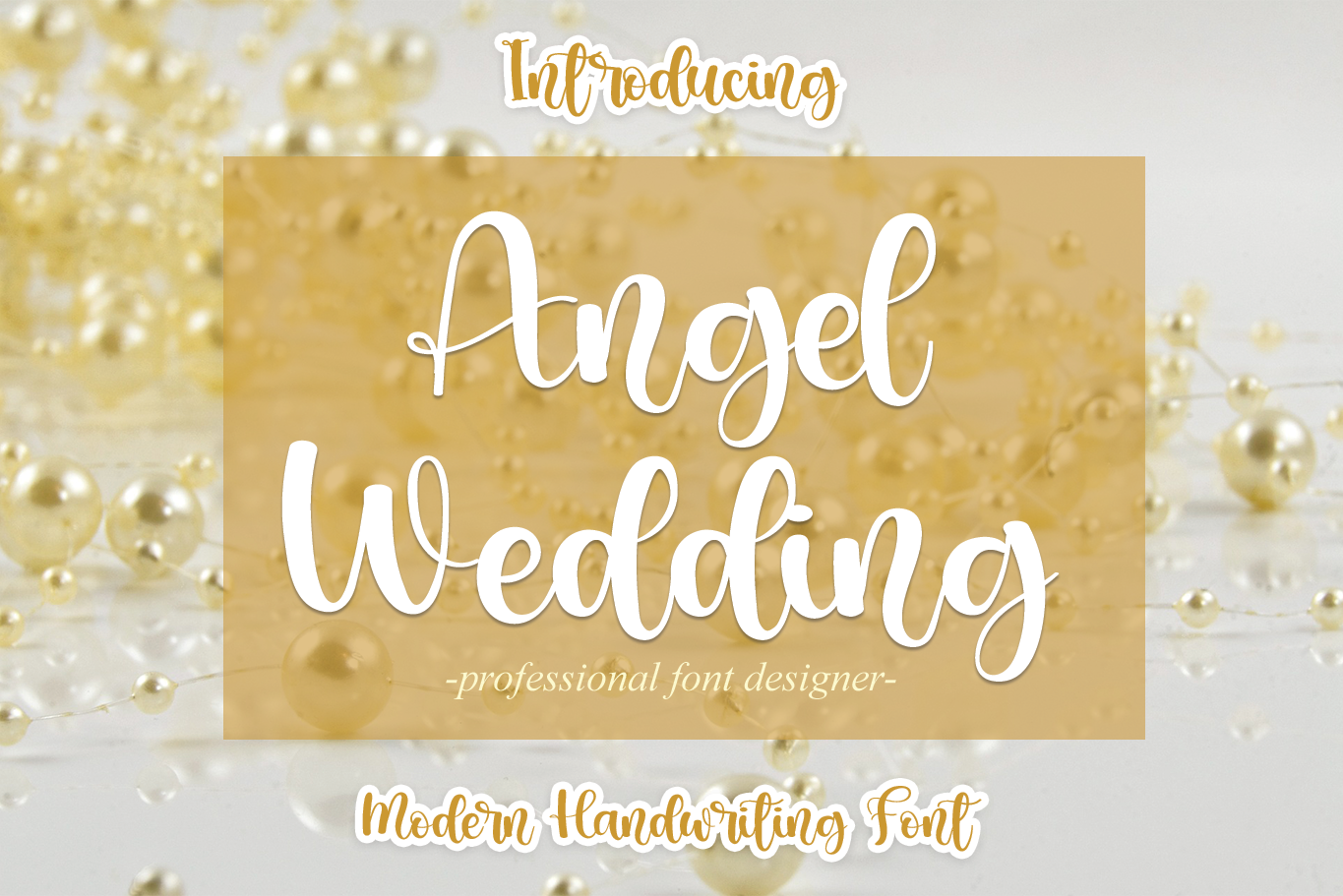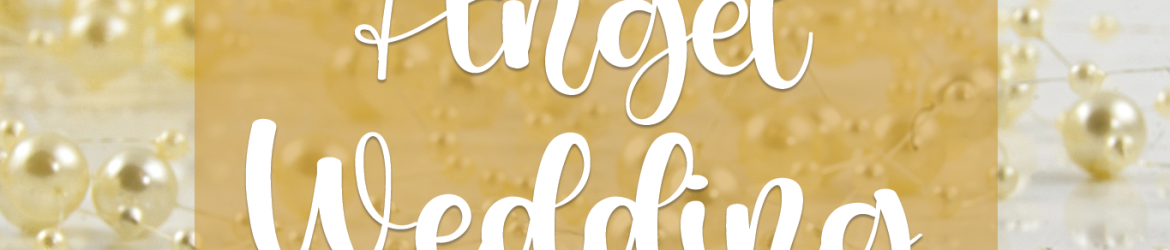
A fonte ‘Angel Wedding’ é uma delicada tipografia script que se destaca por sua elegância e detalhe meticuloso. Perfeita para aqueles desejando um estilo romântico e sofisticado em seus trabalhos, esta font está à disposição de quem busca agregar beleza a qualquer projeto gráfico. Seja ele uma assinatura, um banner ou até mesmo um card de convidado, ‘Angel Wedding’ tem o poder de transformar qualquer criação em algo singularmente bonito e impecável. Com sua rica textura e elegante aparência, é uma escolha inspiradora para aqueles que buscam personalidade para seus materiais. Seja este seu novo aliado na construção de um design memorável, ‘Angel Wedding’ está pronta para transformar a forma como você trabalha com fontes de estilo escritório.